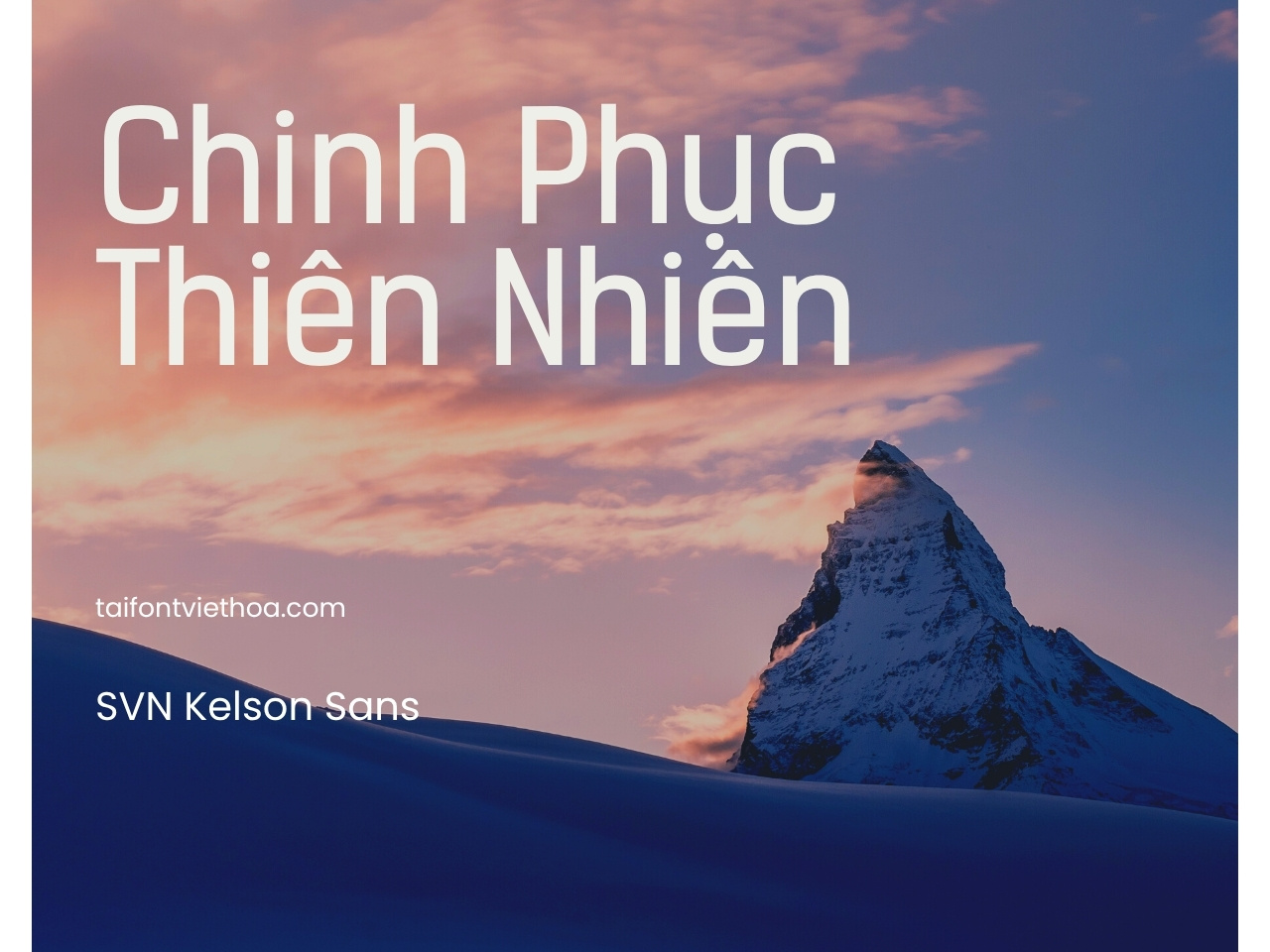
Font việt hóa SVN Kelson Sans đầy đủ
Tác giả Font: Bruno Mello
Giới thiệu về font SVN Kelson Sans Trọn Bộ – Bộ font sans-serif hiện đại, đa dạng và linh hoạt
SVN Kelson Sans là phiên bản Việt hóa của bộ font Kelson Sans – một tập hợp các kiểu chữ sans-serif mang phong cách hiện đại, sạch sẽ và dễ đọc. Bộ font này bao gồm nhiều biến thể từ mảnh đến đậm, phù hợp cho nhiều ứng dụng thiết kế khác nhau, từ thương hiệu đến giao diện người dùng và ấn phẩm truyền thông.
Phiên bản Việt hóa của SVN Kelson Sans Trọn Bộ đã được Taifontviethoa.comtuyển chọn và hoàn thiện, hỗ trợ đầy đủ dấu tiếng Việt cùng hơn 70 ngôn ngữ khác. Font giúp các nhà thiết kế dễ dàng ứng dụng trong các dự án đa dạng, giữ được phong cách hiện đại và linh hoạt.
Đa dạng kiểu dáng – Ứng dụng linh hoạt trong thương hiệu và giao diện
Bộ font SVN Kelson Sans bao gồm các kiểu chữ từ mảnh đến đậm, với các nét chữ rõ ràng, tỷ lệ cân đối và thiết kế tối giản. Font phù hợp sử dụng cho tiêu đề, đoạn văn bản, logo và các ấn phẩm quảng cáo, giúp tăng tính thẩm mỹ và sự dễ đọc trong thiết kế. Phong cách hiện đại và đa dạng của Kelson Sans rất thích hợp với các dự án công nghệ, thương mại điện tử, giáo dục và truyền thông.
Ứng dụng lý tưởng: thiết kế nhận diện thương hiệu, giao diện người dùng, brochure, tài liệu quảng cáo, website, app và các sản phẩm kỹ thuật số. Ngành nghề phù hợp: công nghệ, giáo dục, thương mại điện tử, dịch vụ sáng tạo, startup và các thương hiệu định vị theo phong cách hiện đại, chuyên nghiệp.